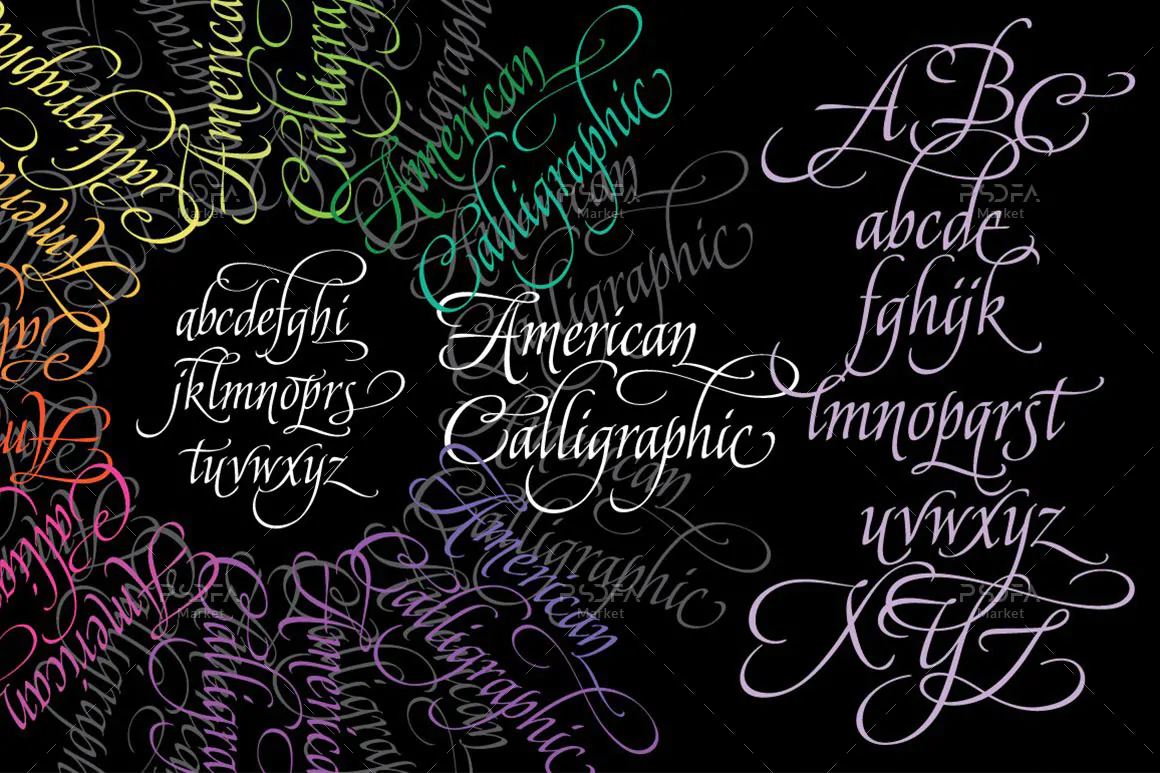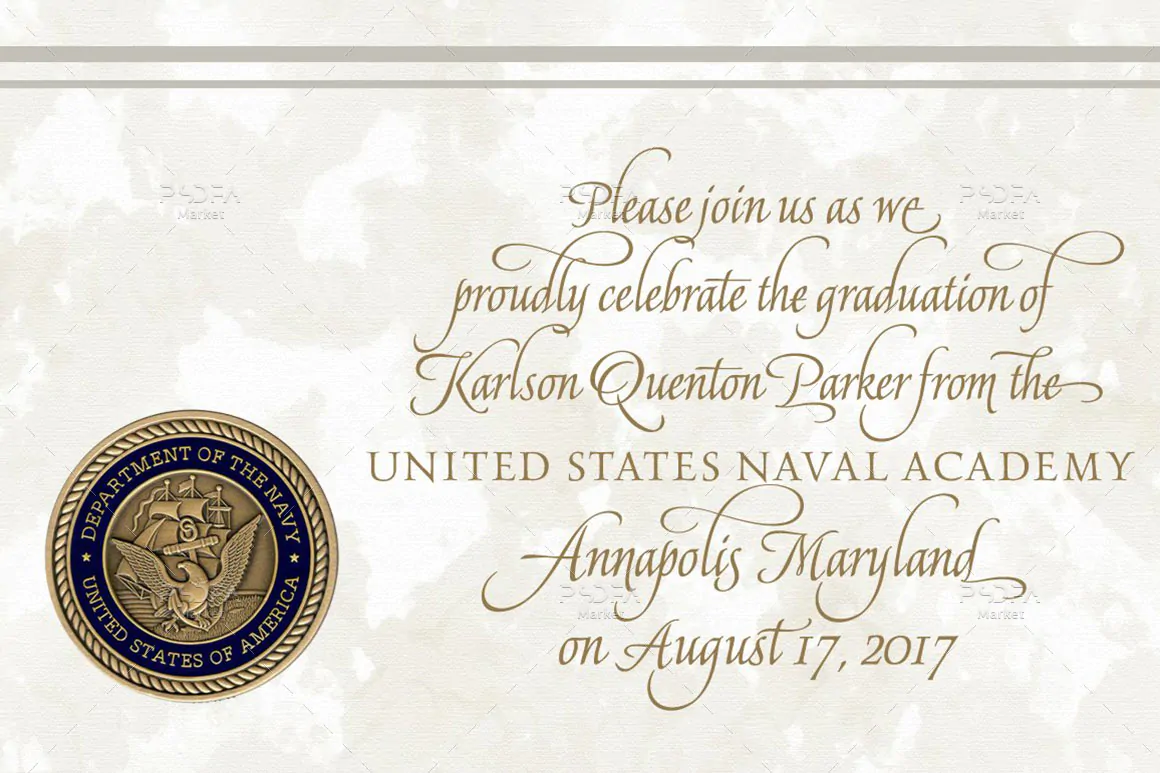
فونت خوشنویسی و کالیگرافی آمریکایی
فونت خوشنویسی و کالیگرافی آمریکایی یک اسکریپت فونت فوق العاده زیبا است که مناسب جهت استفاده در طرح و پروژههای گرافیکی مختلف میباشد. این فونت زیبا با وزن معمولی طراحی شده است که از آن میتوانید در طراحی انواع پوستر، بنر، کارت ویزیت، کارت تبریک، بسته بندی محصولات، قاب عکس، لوازم التحریر و … استفاده کنید.